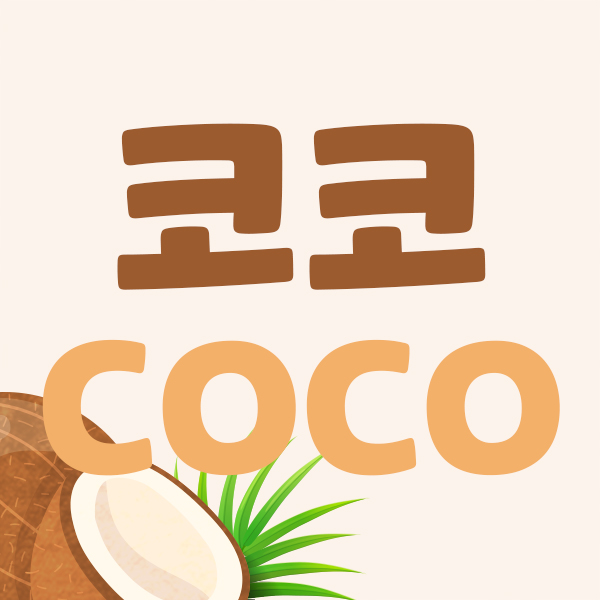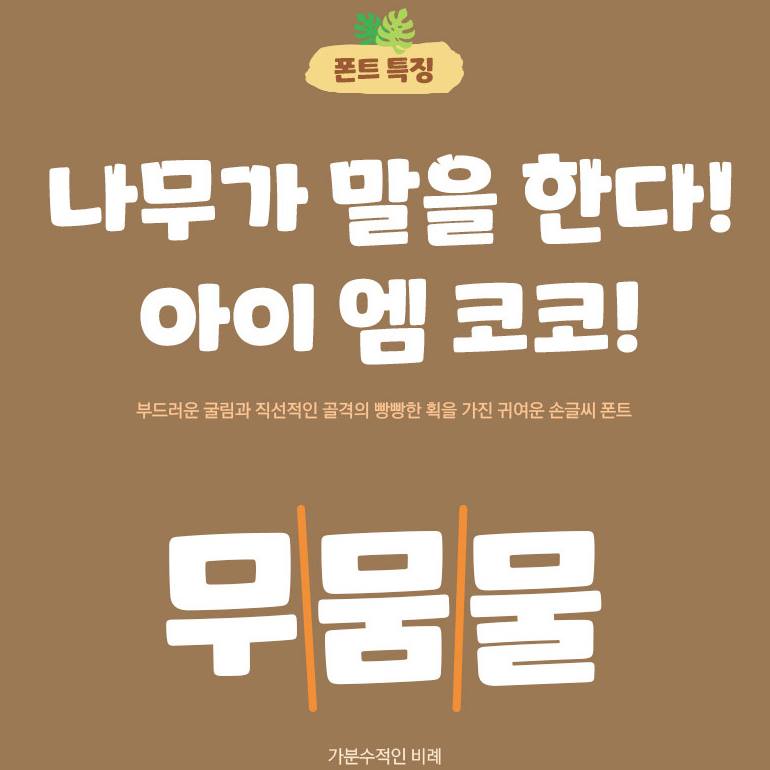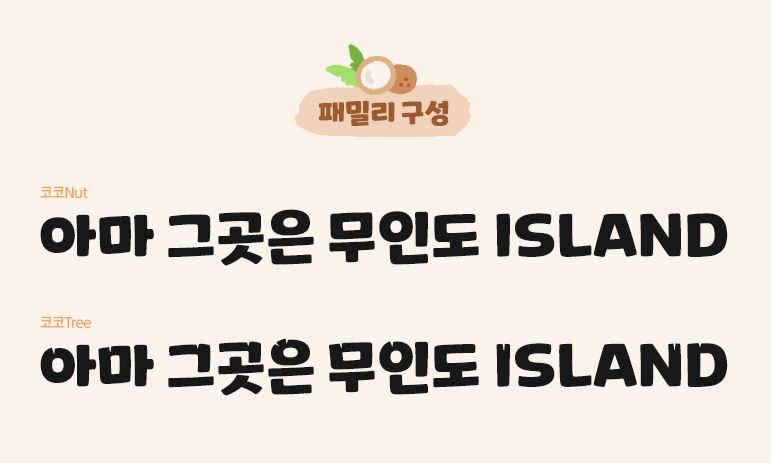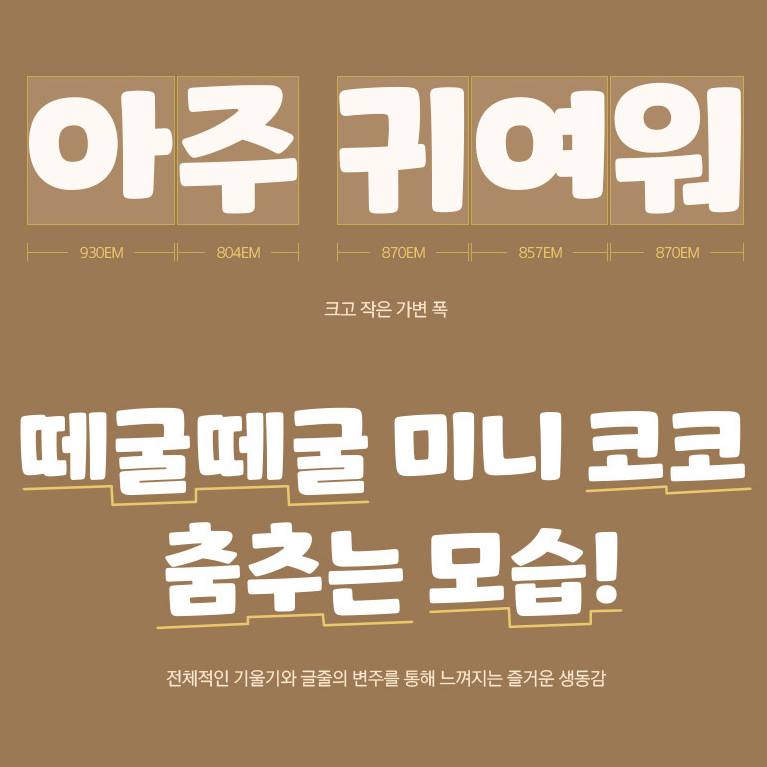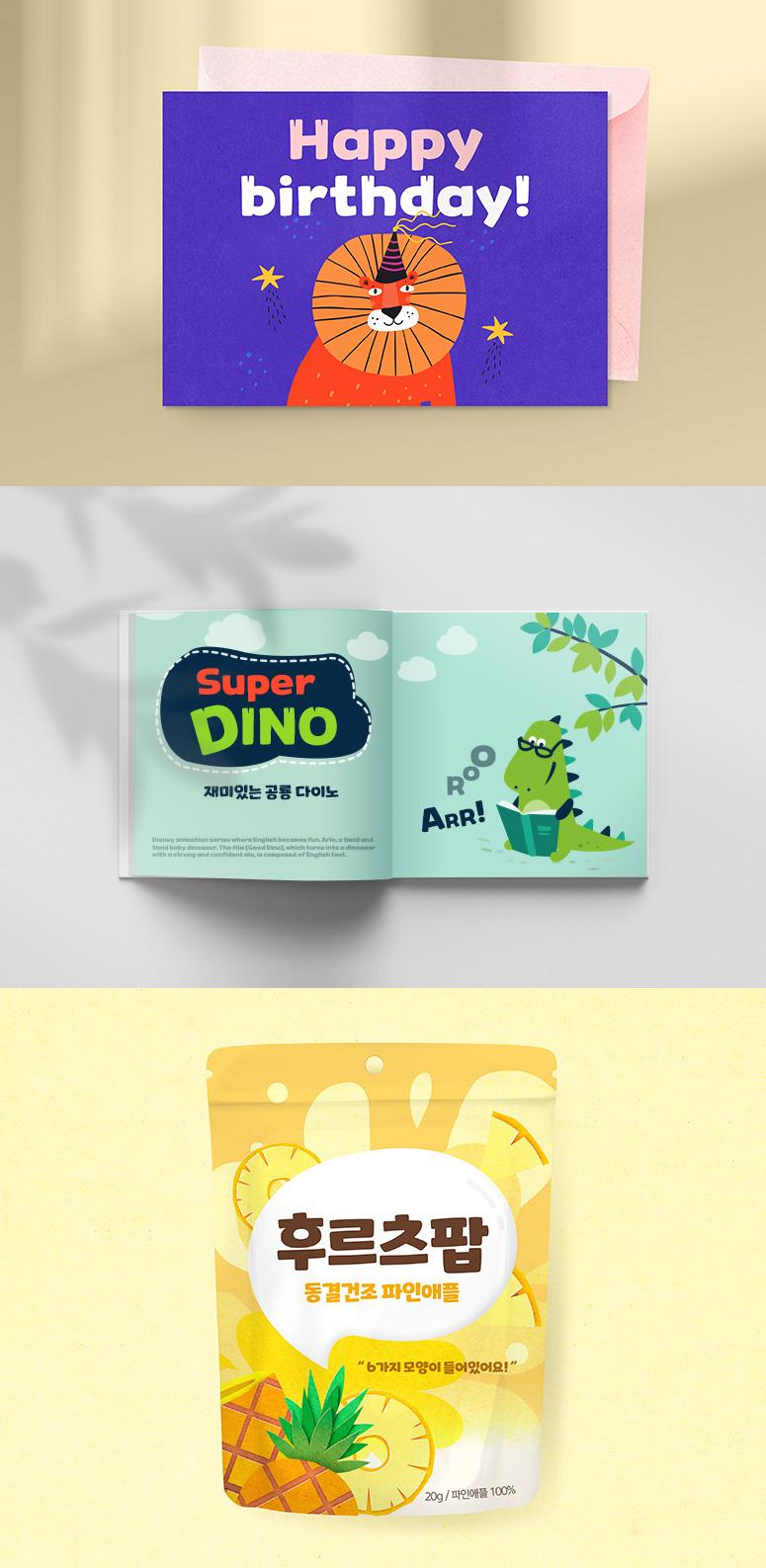
안녕하세요. 릭스폰트 입니다. 이번에 소개해드릴 폰트는 6월의 신서체 동글동글 귀엽고 사랑스러운 「Rix코코」 서체입니다. 이름은 코코넛 나무에서 착안했는데요~ 폰트를 디자인해 주신 김근영 디자이너님의 인터뷰 먼저 들어보실게요:)
폰트를 알려면 디자이너를 알아야지_폰트 디자이너 인터뷰
안녕하세요. 자기소개 부탁드려요!
글자 만드는 것이 너무나 재미있는 김근영입니다. 한 글자 한 글자 즐거운 마음으로 만들고 있어요. 이런 제 마음이 글자에서 느껴졌으면 좋겠어요. 개인적으로 부드럽고 안정감 있는, 편안한 분위기가 나는 폰트들을 좋아해요.
Rix코코 폰트는 어떻게 기획하게 되었나요?
편하게 많이 쓸 수 있는 폰트를 만들고 싶었어요. 친근함과 캐주얼함, 캐릭터 같은 생동감을 담아보자 했습니다. 유튜브 자막이나 프로그램 자막 등에 편하게 쓸 수 있게끔요!
작업 과정에서 중요하게 생각한 것은 무엇인가요?
즐거운 마음으로 작업하기! 작업하는 내내, 만약 코코가 살아있는 생명체라면 볼 꼬집해주고 싶었어요. 재미있게 애정 듬뿍 담은 마음이 폰트에서도 다 느껴지지 않나요?◡‿◡✿
디자인 과정에서는 글자 하나 하나의 완벽함에 집중하기보다, 전체적인 분위기를 더 중요하게 생각했어요. 기울기에 글줄의 변주도 있다 보니 자연스럽게 어우러져야 했고, 귀여운 느낌을 위해서는 전체적인 분위기를 보는 것이 더 중요했던 것 같아요.
코코 폰트의 가장 큰 매력은 무엇이라고 생각하시나요?
말해 뭐해~! 보고만 있어도 웃음이 지어지는 귀여움!
정말 폰트가 귀여워요(웃음) 'Rix코코' 서체가 어떻게 쓰였으면 좋겠나요?
캐릭터계에는 뽀로로가 있다면 폰트계에는 코코! 가 되길 바랍니다!ㅎㅎㅎ 많은 분들이 코코를 귀여워해 주시면 좋겠어요. 친근하고 캐주얼한 분위기이기 때문에 편하게 쓰일 것 같아요. 친한 친구랑 노는 느낌으로 즐겁게 사용해 주시면 행복할 것 같습니다!
둥글둥글 손글씨의 개성이 듬뿍 담긴, "Rix코코"
새롭게 선보인 Rix코코 폰트는, 두껍고 둥글둥글한 특징을 갖고 있는데요~
손글씨만의 개성과 나무의 질감을 살려 독특하고 귀여운 서체입니다:)
이 폰트는 특별히 두 가지 스타일로 제작되었어요.
기본 스타일은 코코Nut 그리고 나무 질감을 추가한 코코Tree
이름도 쏘 큐트,,♥
코코 하니까, 영화 <코코> 떠오르신 분!
영화의 따뜻하고 몽글몽글한 분위기와도 왠지 어울리는 느낌이에요.
| Rix코코 적용 이미지 샘플
Rix코코 서체는 디자이너님도 말씀하신 것처럼 친근한 매력이 있는 만큼 귀여운 이미지들과 함께 구성하기 좋고 광고, 유튜브 등 영상 매체에 제목이나 자막으로도 활용도가 높답니다.